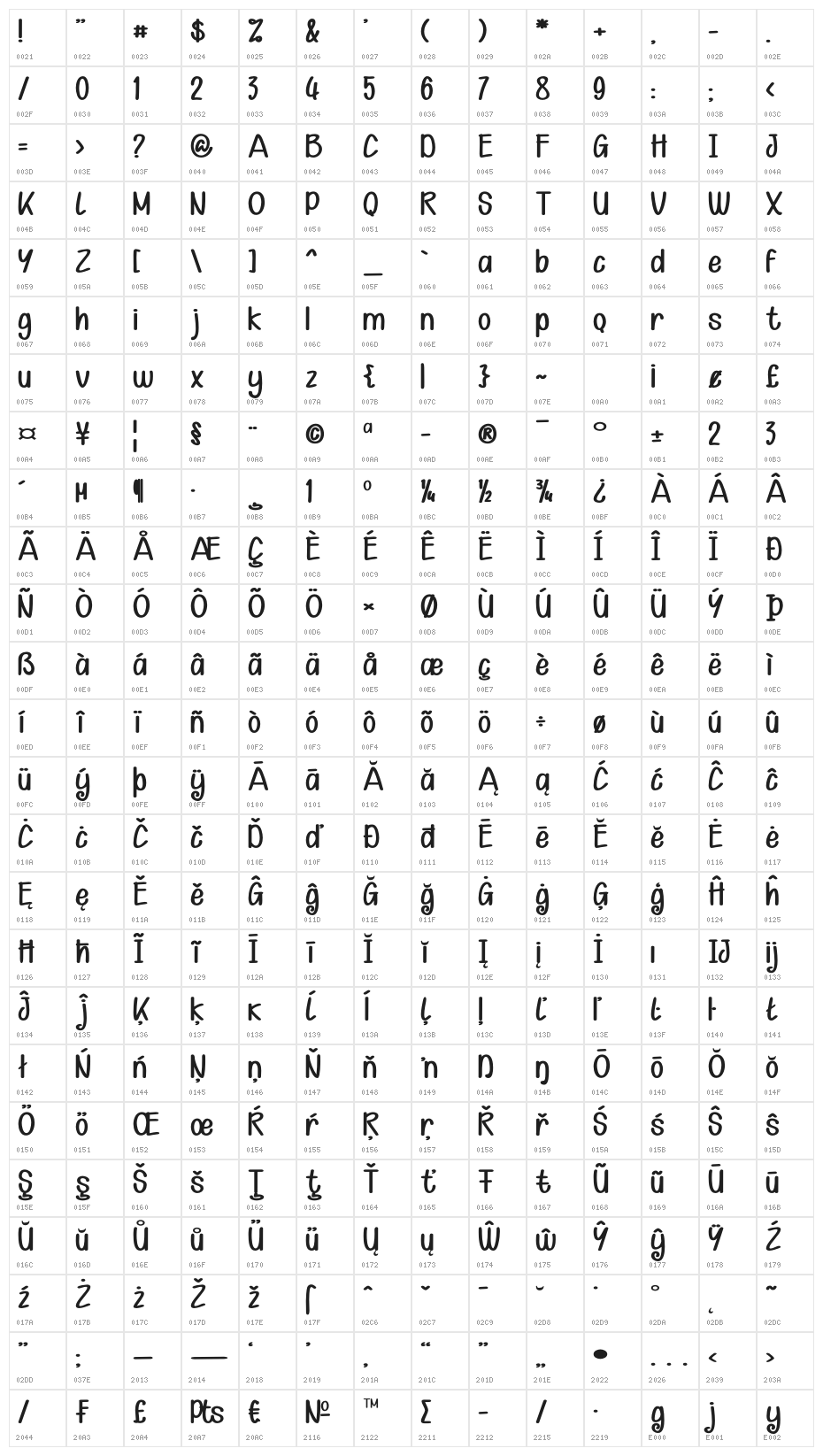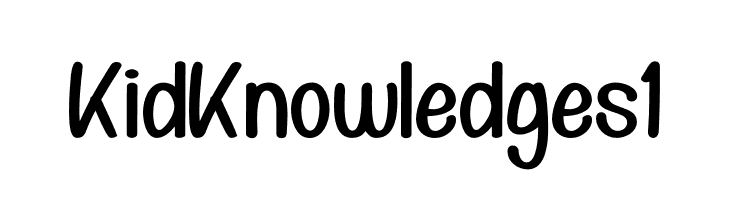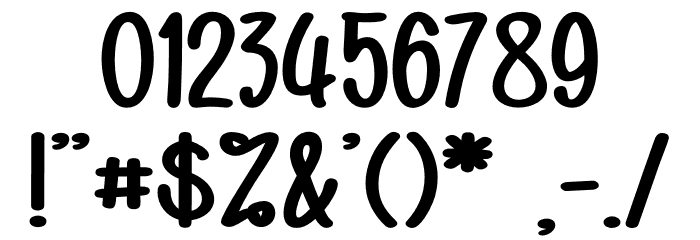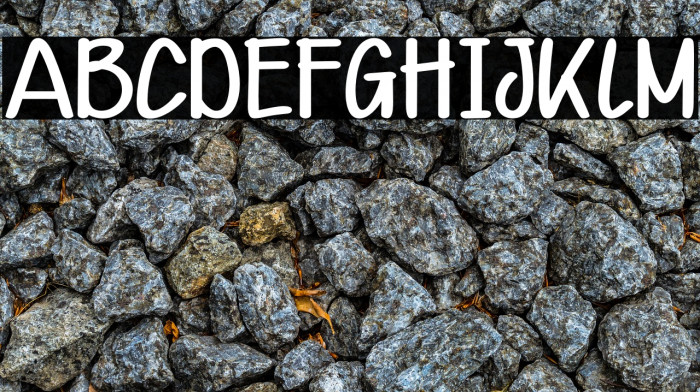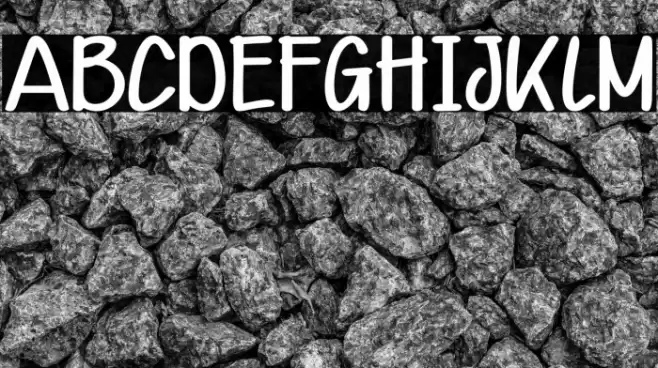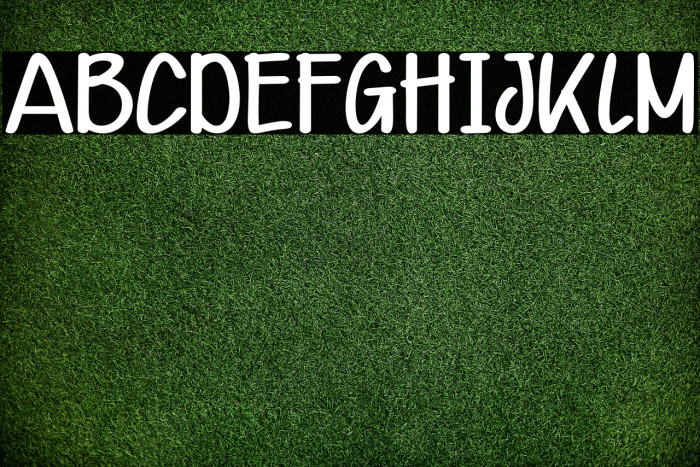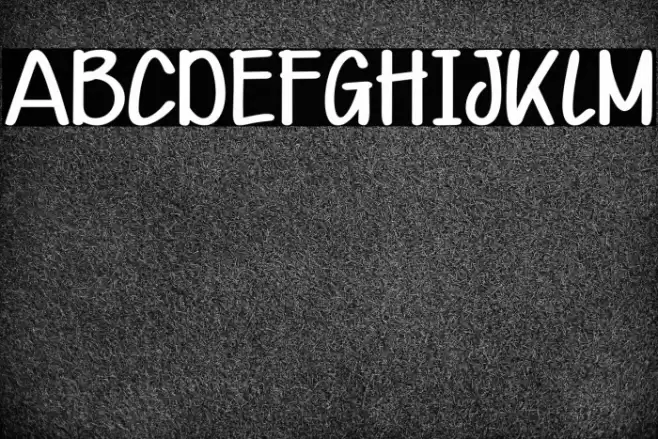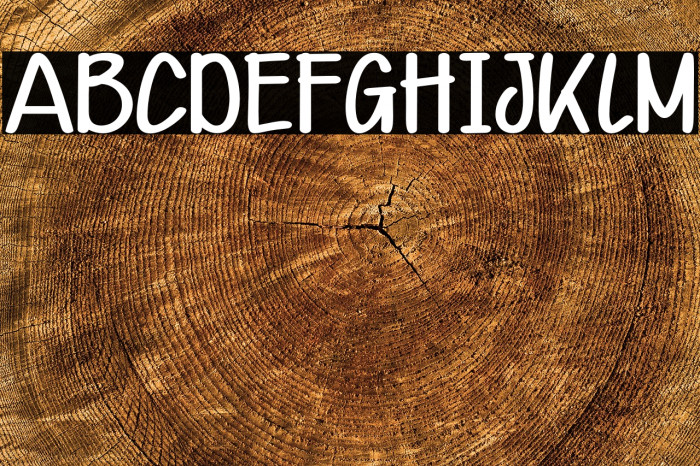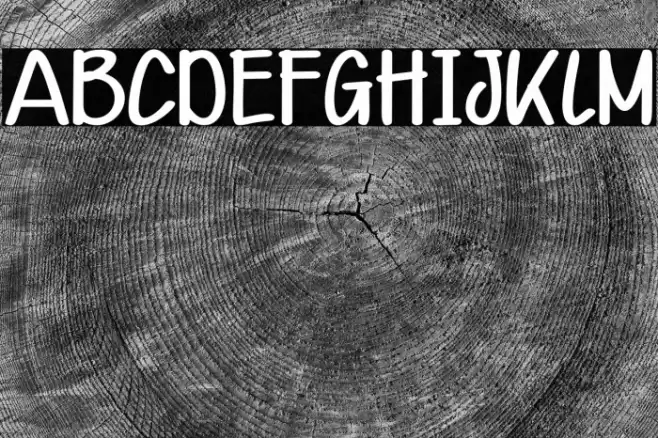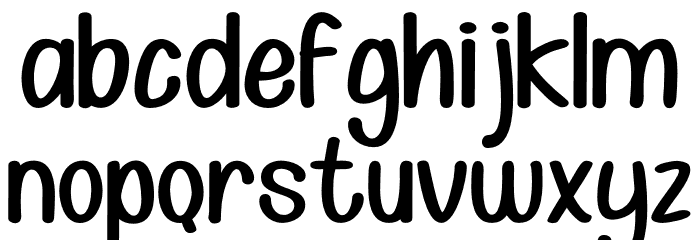
Kid Knowledges 1 Font
✎ Comic
| カテゴリ | Comic |
| おすすめプロジェクト | Ideal for children's books, playful branding, casual invitations, and creative posters. |